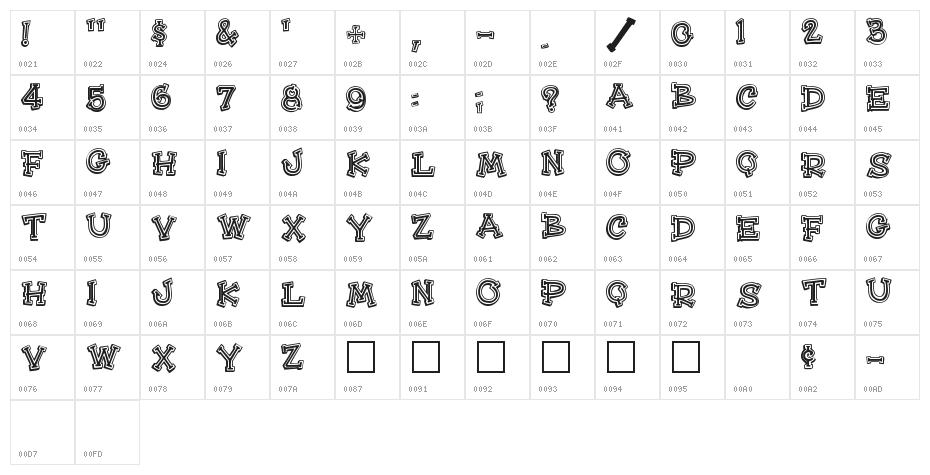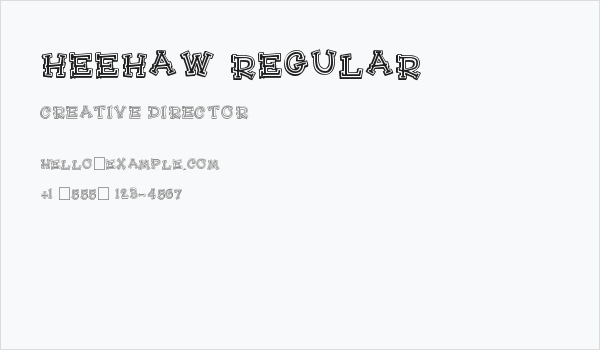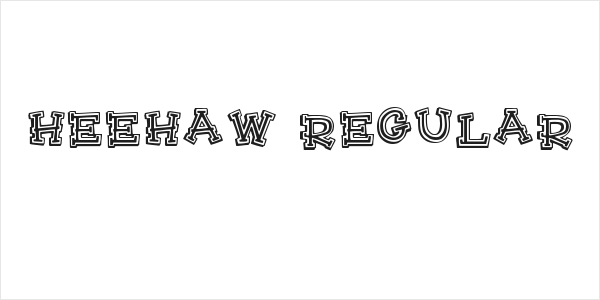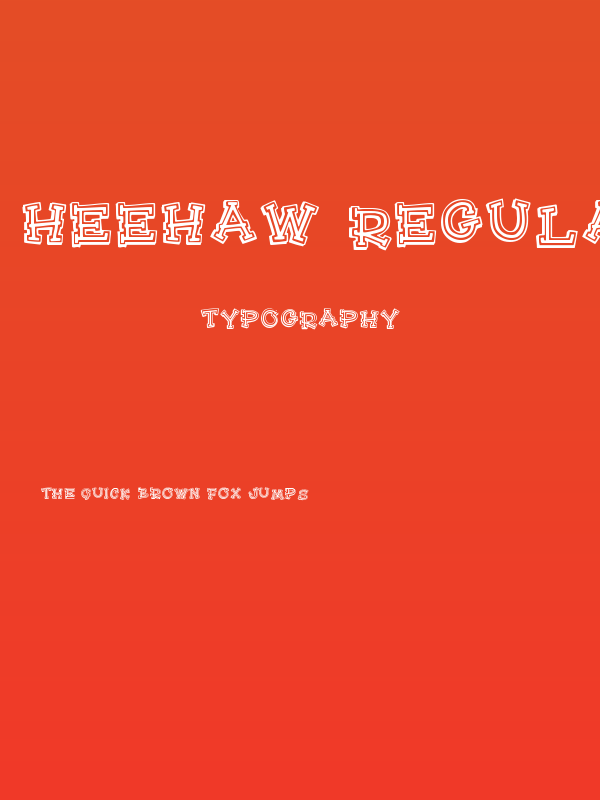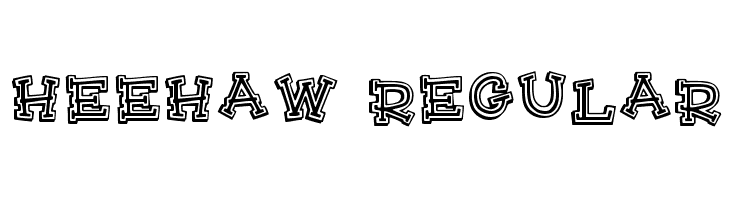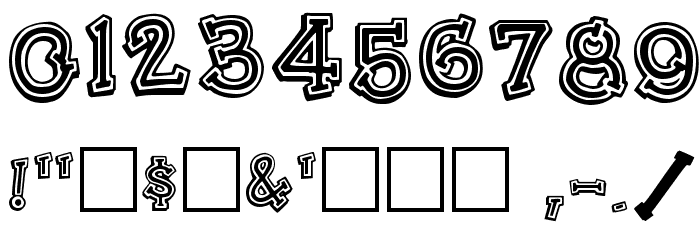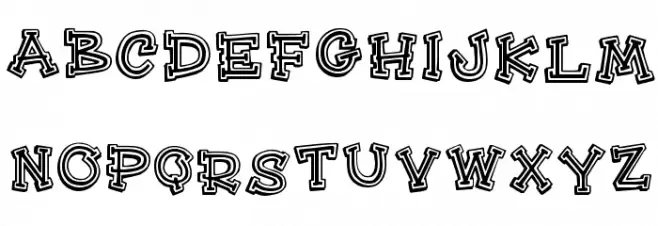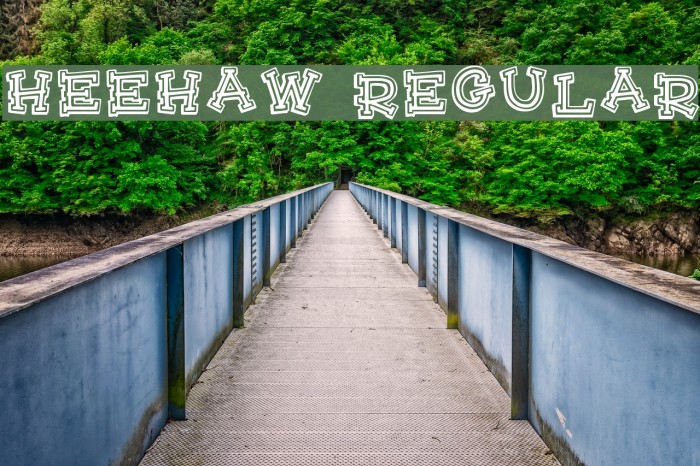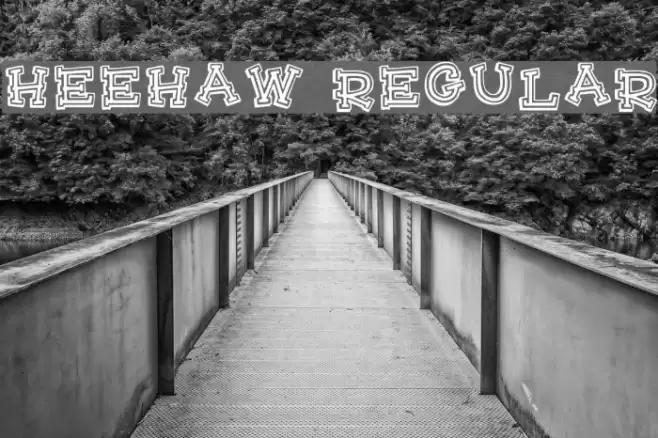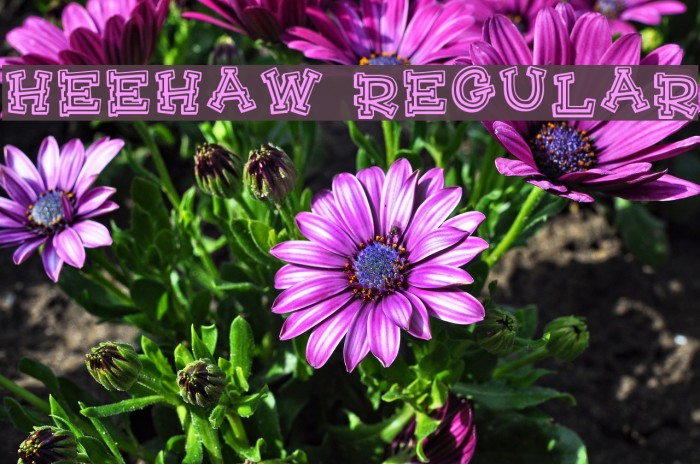
HeeHaw Regular Font
✎ Western
| Catégories | Western |
| Style général | Playful, Whimsical |
| Projets proposés | Ideal for children's books, playful branding, party invitations, and eye-catching headlines. |